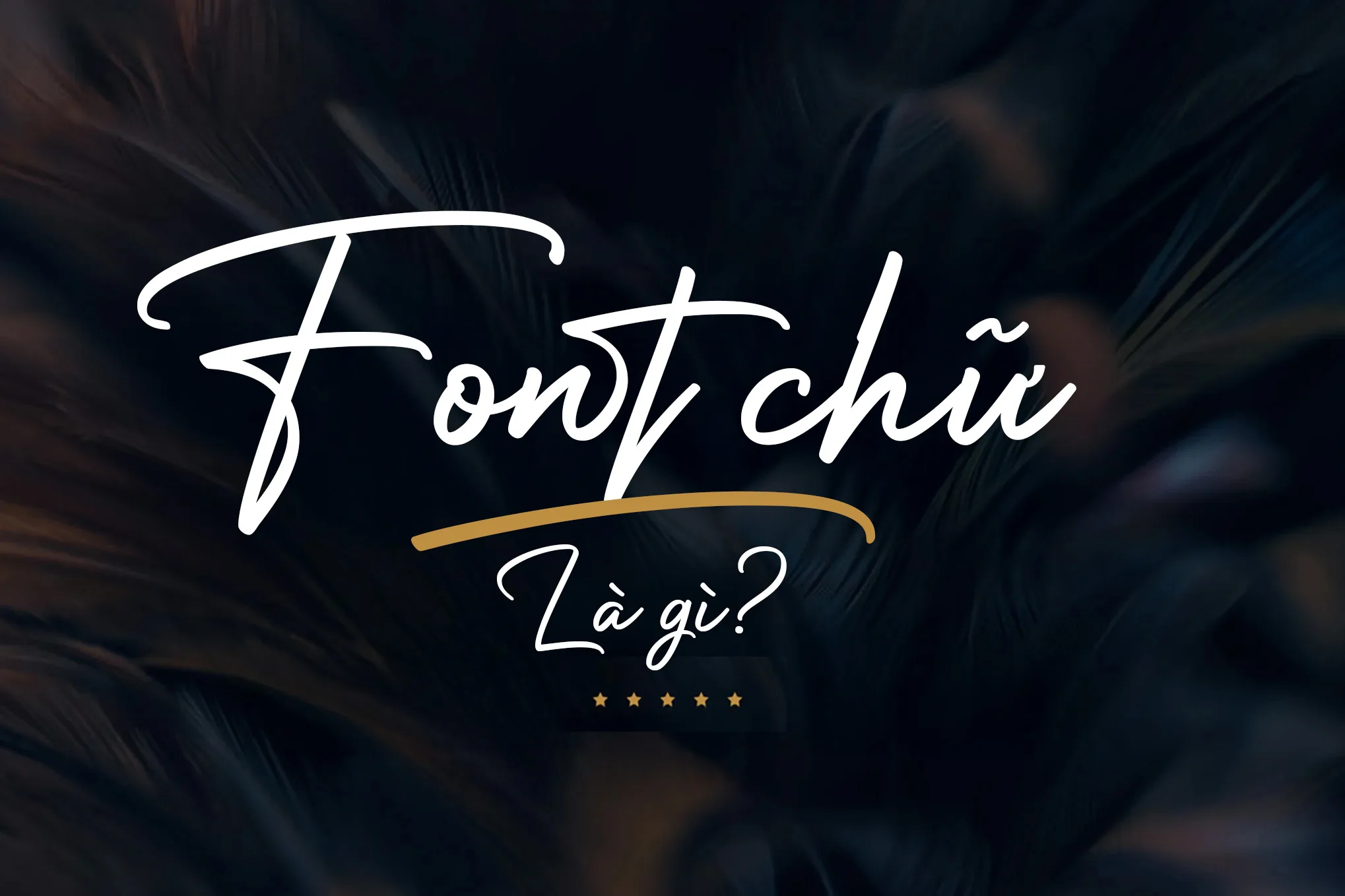
Font chữ là gì? Phân biệt giữa Font, Typeface và Glyph
Font chữ là một yếu tố quan trọng trong thiết kế đồ họa và truyền thông. Tuy nhiên, nhiều người thường nhầm lẫn giữa các thuật ngữ Font, Typeface và Glyph. Trong bài viết này, chúng ta sẽ làm rõ sự khác biệt giữa các khái niệm này để giúp bạn hiểu rõ hơn về thế giới typography.
1. Font chữ là gì?
Font chữ (Font) là tập hợp các ký tự có cùng phong cách thiết kế, bao gồm chữ cái, số, dấu câu và ký hiệu đặc biệt. Font chữ quy định cách hiển thị của nội dung văn bản trên các phương tiện kỹ thuật số và in ấn.
🔹 Ví dụ: Arial, Times New Roman, Roboto, Montserrat đều là các font chữ.
2. Phân biệt Font, Typeface và Glyph
2.1. Typeface là gì?
Typeface (Bộ chữ) là một thiết kế tổng thể của một nhóm font chữ có cùng phong cách. Nó bao gồm nhiều font chữ với các biến thể khác nhau như đậm (Bold), nghiêng (Italic), mỏng (Light), v.v.
✅ Ví dụ:
• Helvetica là một typeface, nhưng nó có nhiều font như Helvetica Regular, Helvetica Bold, Helvetica Italic.
• Times New Roman là một typeface, bao gồm các font như Times New Roman Regular, Times New Roman Bold, Times New Roman Italic.
📌 Tóm lại: Typeface là tổng thể thiết kế, còn Font là một biến thể cụ thể của typeface đó.
2.2. Glyph là gì?
Glyph là một hình dạng cụ thể của một ký tự trong một font chữ. Mỗi ký tự có thể có nhiều glyph khác nhau tùy theo ngữ cảnh hoặc thiết kế.
✅ Ví dụ:
• Chữ “A” trong một font chữ có thể có nhiều phiên bản khác nhau (chữ hoa, chữ thường, chữ viết tay, chữ trang trí, v.v.).
• Một số font hỗ trợ nhiều ngôn ngữ sẽ có các glyph thay thế để phù hợp với ký tự đặc biệt.
💡 Nói cách khác, Glyph là đơn vị nhỏ nhất trong hệ thống font chữ, là cách một ký tự cụ thể được hiển thị.
3. Tổng kết sự khác biệt
Thuật ngữĐịnh nghĩaVí dụ
TypefaceBộ thiết kế tổng thể của một nhóm font chữHelvetica, Times New Roman, Roboto
FontMột biến thể cụ thể của typeface với trọng lượng, kích thước khác nhauHelvetica Bold, Helvetica Light, Helvetica Italic
GlyphHình dạng cụ thể của một ký tự trong một font chữChữ “A” có thể có nhiều kiểu viết khác nhau
4. Tại sao hiểu rõ các khái niệm này lại quan trọng?
• Giúp bạn chọn font chữ phù hợp cho thiết kế.
• Hiểu rõ cách sử dụng font chữ để tạo bố cục hài hòa.
• Tránh nhầm lẫn khi làm việc với typography trong thiết kế đồ họa và web.
• Giúp tìm kiếm font chữ dễ dàng hơn khi tải về hoặc mua font.